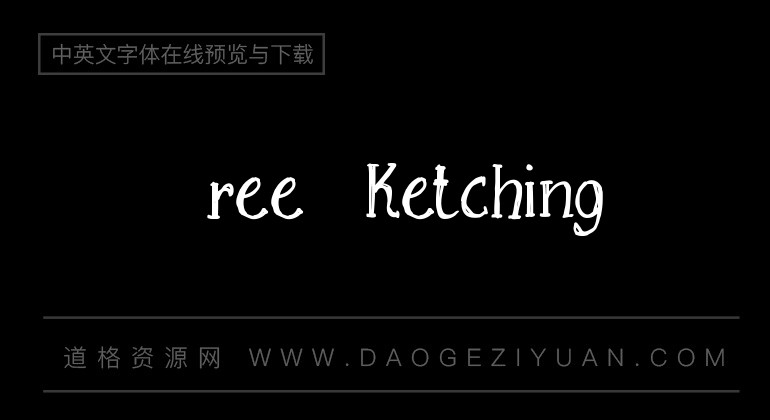
Free Sketching
Free Sketching 是一种手绘风格的字体,它是由字母、数字和一些符号组成的,每个字符都像是手工绘制的。这种字体可能会让人想起儿童绘画或草图,因为它们都有一种自由、轻松和随意的感觉。 Free Sketching 字体非常适合用于设计项目,比如海报、广告、名片、包装等。它可以增加设计的趣味性和独特性,而且也很容易吸引人的注意力。 此外,Free Sketching 字体也非常适合用于一些手工或艺术相关的项目,比如手写笔记、手工卡片等。这种字体会让文字看起来更加有趣,也能够传达一种自然、温暖和亲切的感觉。 总之,Free Sketching 字体是一种很有趣的字体,它适合用于多种场合和项目,如果你想要增加设计或文字的趣味性,不妨尝试一下这种字体。
Free Sketching是一款非常不错的手写艺术字体,具有很好的视觉感,适合于文化类的宣传设计、商业类品牌的广告和产品包装设计以及个性化文字排版等较多场景。